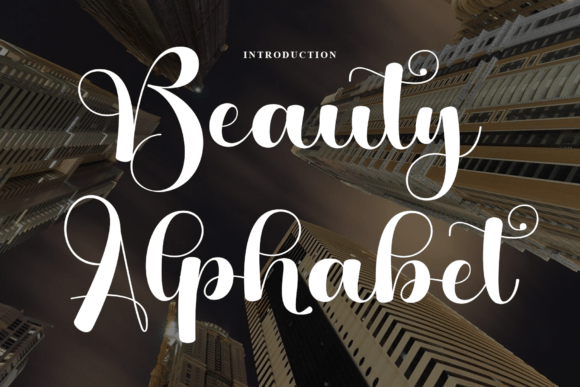
Beauty Alphabet
Beauty Alphabetのような高品質の素材をお探しの場合、このプレミアムパッケージはクリエイティブなプロジェクトに素晴らしい選択です。
POD(オンデマンド印刷)製品、結婚式の招待状、またはソーシャルメディアのグラフィックを作成している場合でも、Beauty Alphabetは理想的です。